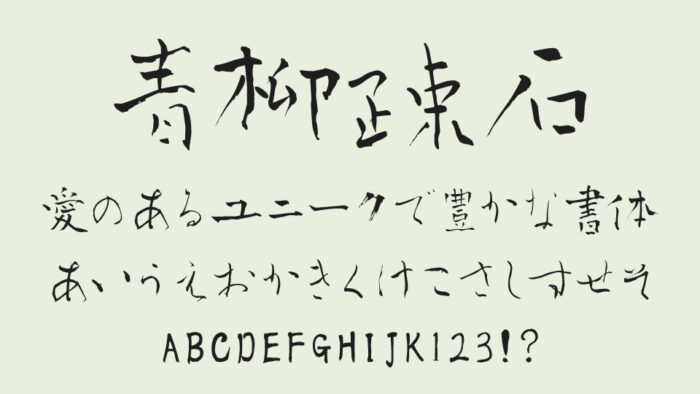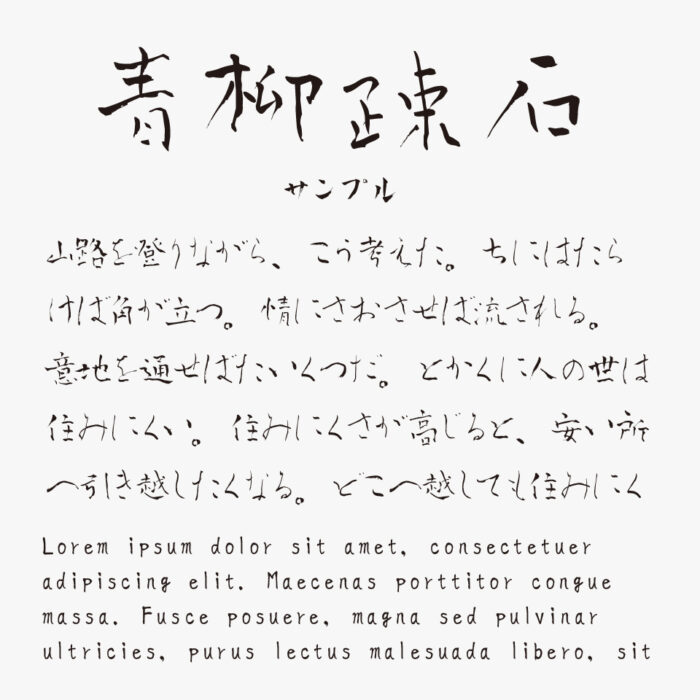
青柳疎石フォント
青柳疎石フォントは、書家の青柳疎石先生が字母を書かれ、青柳衡山様がフォント化された毛筆フォントです。
筆跡の濃淡や揺らぎがリアルに表現された、味わいのある古典的で風格のある筆文字の手書きフォントです。かすれやインクのにじみが繊細にフォントに再現されているため、まるで和紙に筆で綴られたような味わい深さのあるフォントとなっています。
収録文字は、漢字(JIS非漢字、JIS第一水準漢字、JIS第二水準漢字)・ひらがな・カタカナ・アルファベット・数字・記号が収録されています。